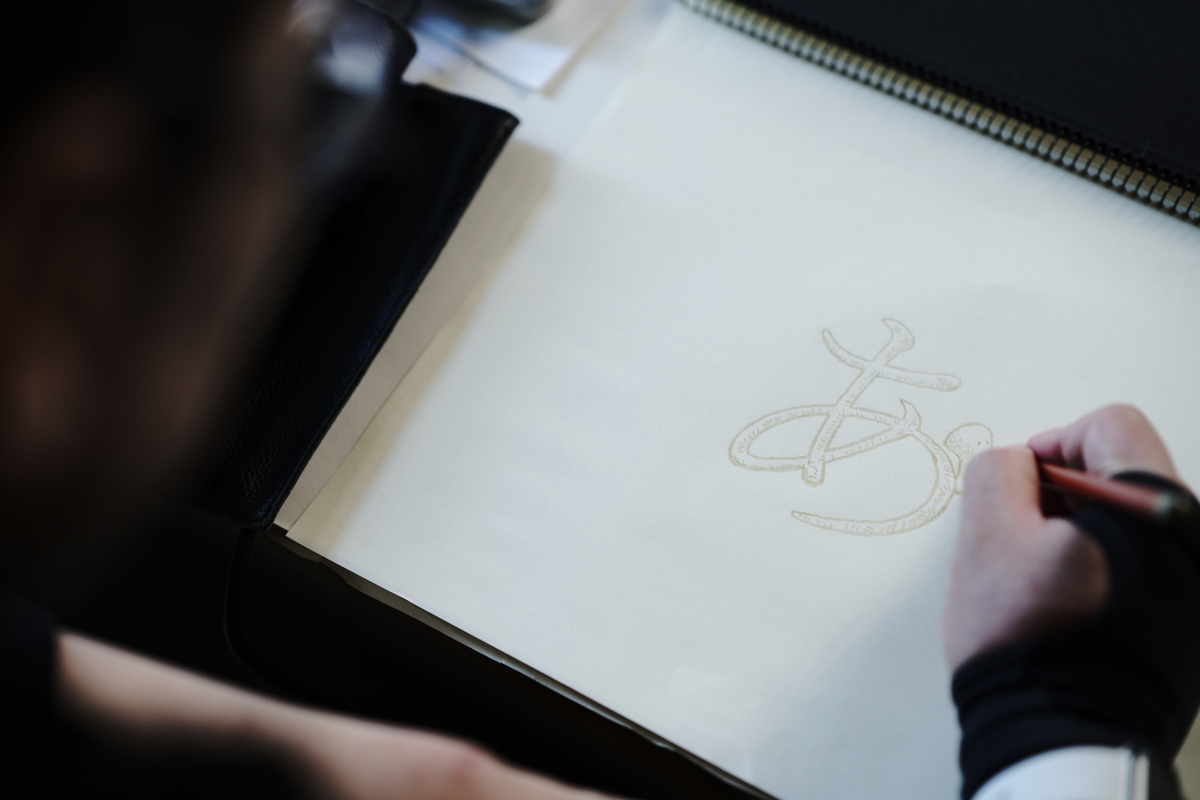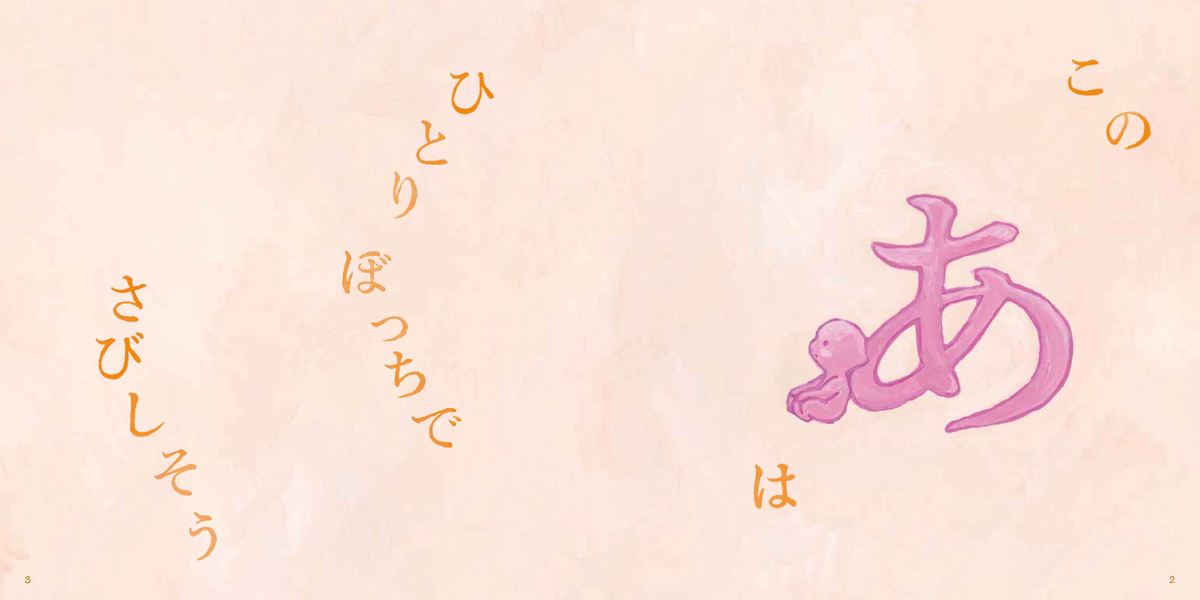
ひらがなあそびの絵本「あ」
アリス館から2020年8月28日に谷川俊太郎氏の書き下ろし新作で絵を広瀬弦氏が担当した、ひらがなあそびの絵本「あ」が発売された。好評につき発売前重版も決定した。
あ は一人ぼっちでさびしそう。
だれか ともだち いないかな?
文字と文字の組み合わせで、言葉が生まれ、物語が生まれる。
その楽しさが、絵本になった。
ひらがなあそびの絵本「あ」みどころ
谷川俊太郎氏の書き下ろし!
文字と文字で、言葉が生まれる喜びを伝える。
谷川俊太郎氏は「あ」と何を組み合わせたら子どもたちが楽しめるものになるか、絵にして楽しいものは何か、考えながら文にしたとのこと。
制作過程を振り返りつつ、
「二文字の文ははじめて。制約が多くて大変だもの」とコメントしている。
広瀬弦氏の美しい文字と絵
上下左右に楽しげに動く文字で、言葉の魅力を伝える。
文字を「もの」として捉えてほしくて、縦書きになったり横書きにしたりしてみたという、広瀬弦氏。
「子どもたちに1ページずつ、楽しんでもらえたらいいな」とコメントしている。
制作の過程で生まれた、文字の妖精「かなちゃん」。
かなちゃんが、文字たちの気持ちを表現していく。
「本ができたのは、かなちゃんのおかげ」と、谷川俊太郎氏。
この小さな存在が、じつは本では大きな役割を果たしている。
「あ」はひとりぼっちで さみしそう。でも……
「あ」と「お」が出会って……あおぞらに!
「あ」のところに「し」がやってきて……「あし」だ! どこへでもいけるよ!